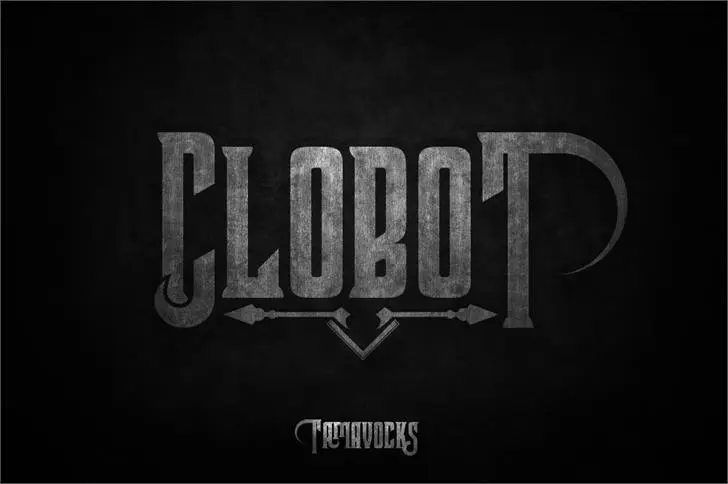
A Clobot Free Font é uma fonte gótica que oferece um design elegante e sofisticado para seus projetos digitais. Ela foi criada pelo designer Hamilton, proporcionando uma experiência visual única para textos de alto impacto. Seu estilo arcaico, mas ainda moderno, dá às palavras uma qualidade inovadora sem perder a beleza tradicional da gíria gótica. Para usuários que valorizam o uso de fontes gratuitas e pessoais, esta é uma ótima escolha. Para aqueles que buscam uma fonte comercialmente viável, Hamilton oferece a opção para adquirir as licenças completas através do site mencionado no texto da descrição original.